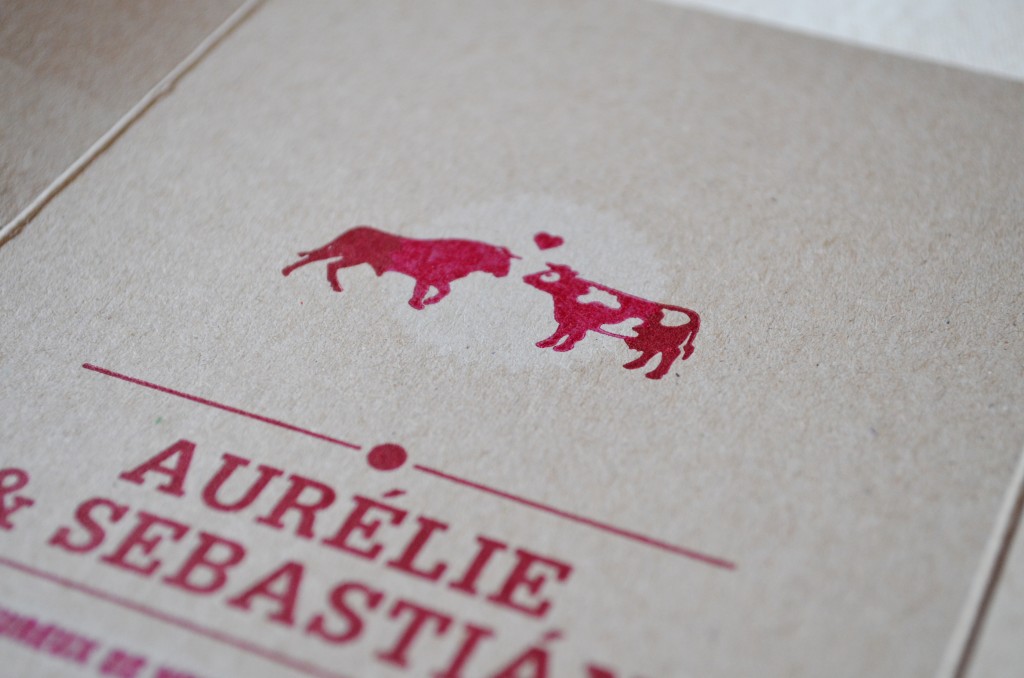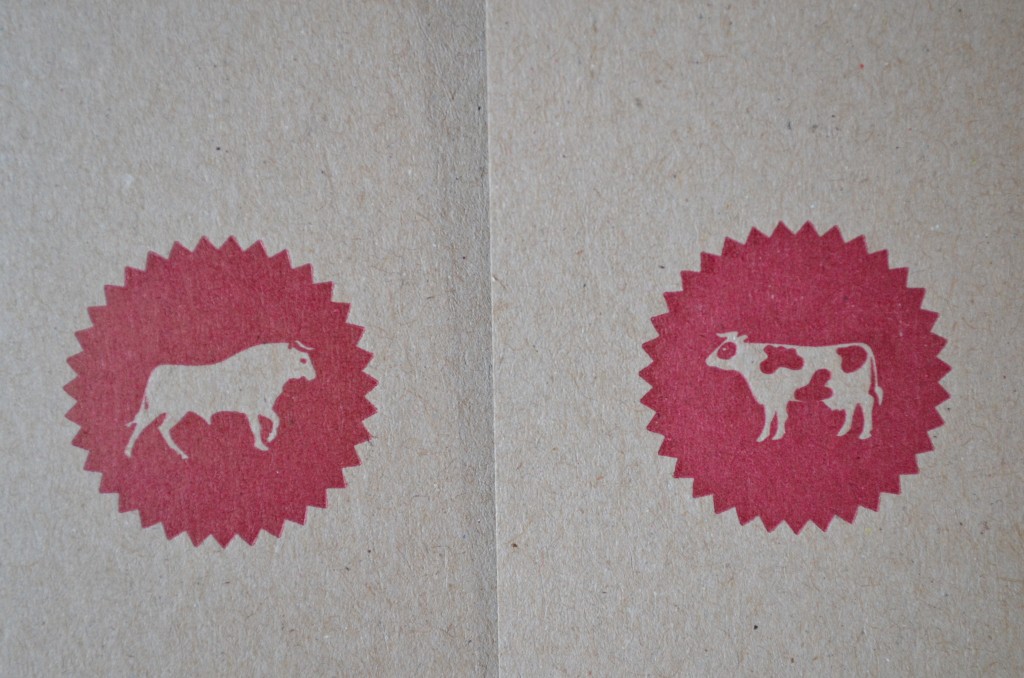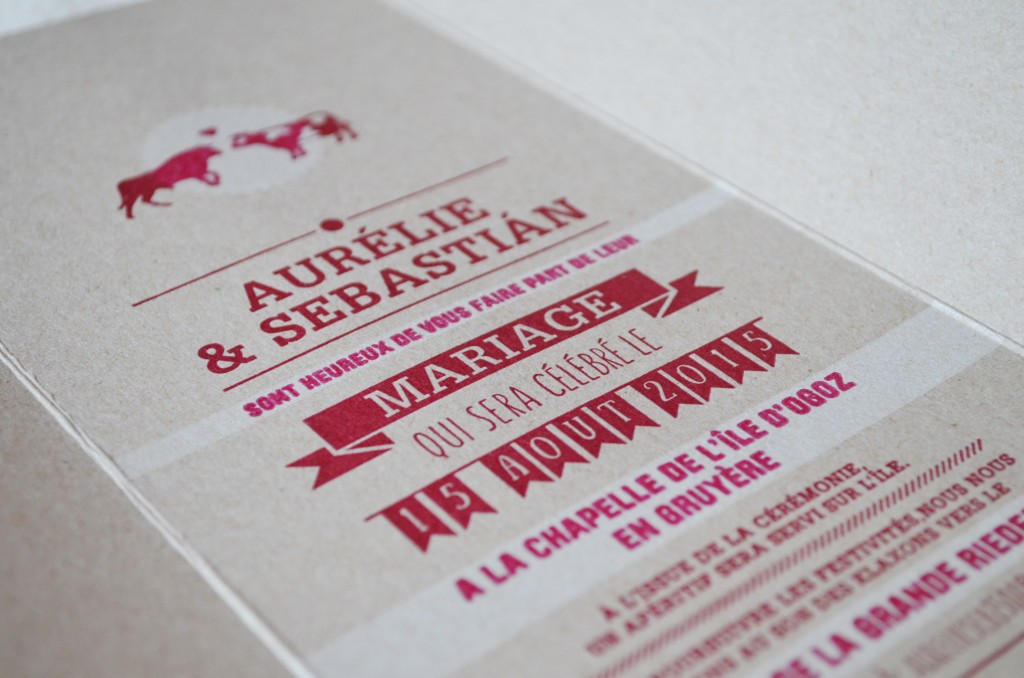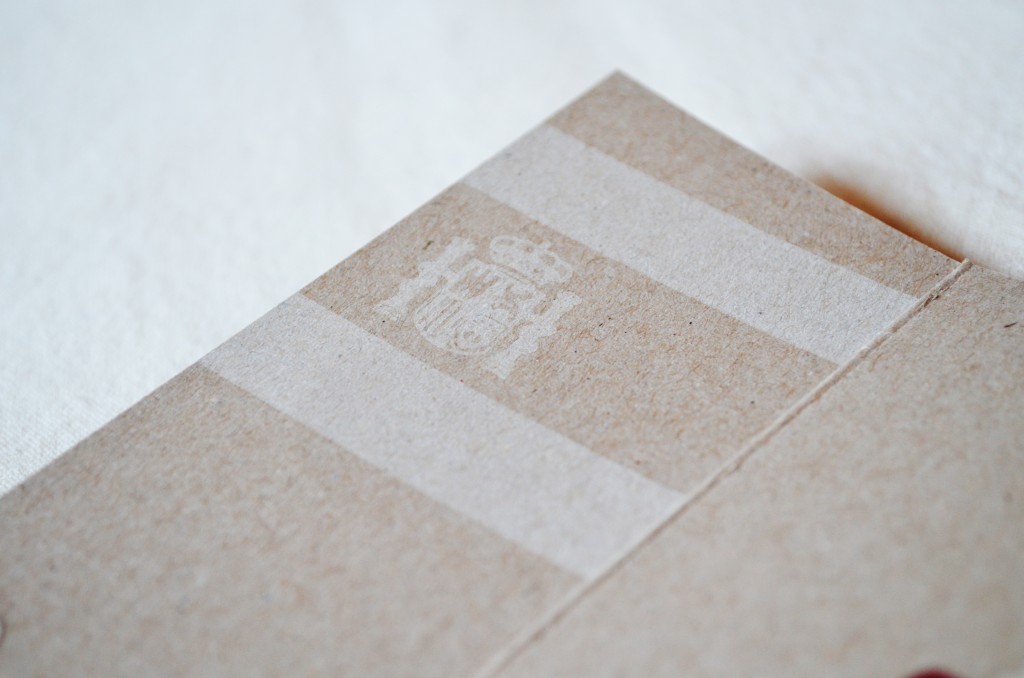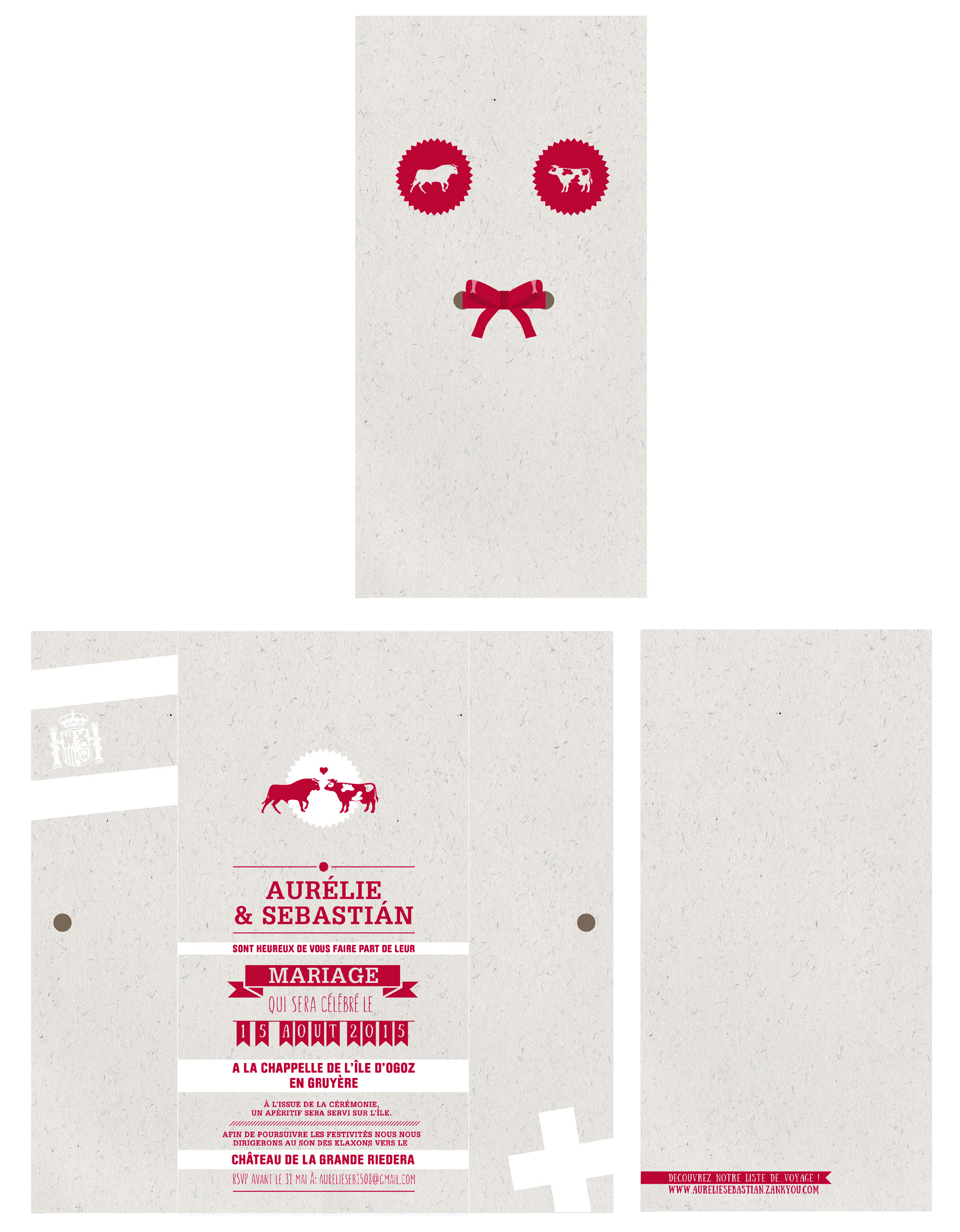
Réalisation d’un faire part pour un mariage entre un Espagnol et une Suissesse. Utilisation de la symbolique de la vache suisse et du «toro» espagnol, en accord avec un mix typographique.
Impression en letter press à l’atelier typographique «Le Cadratin», Vevey.